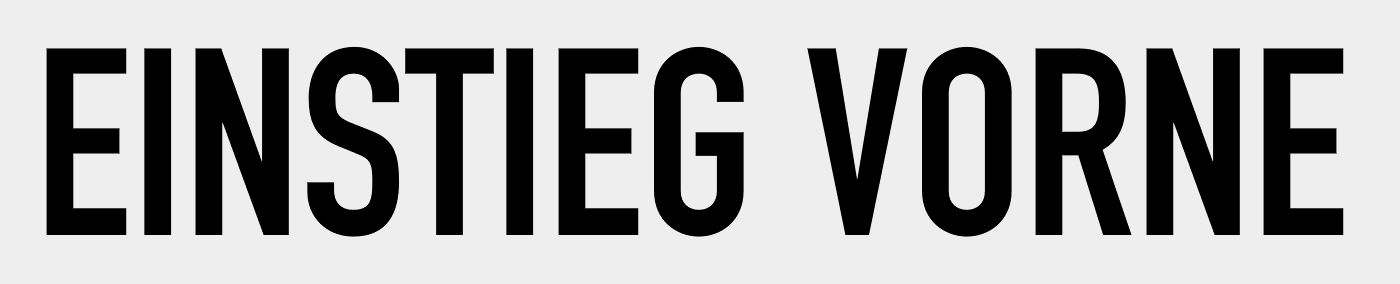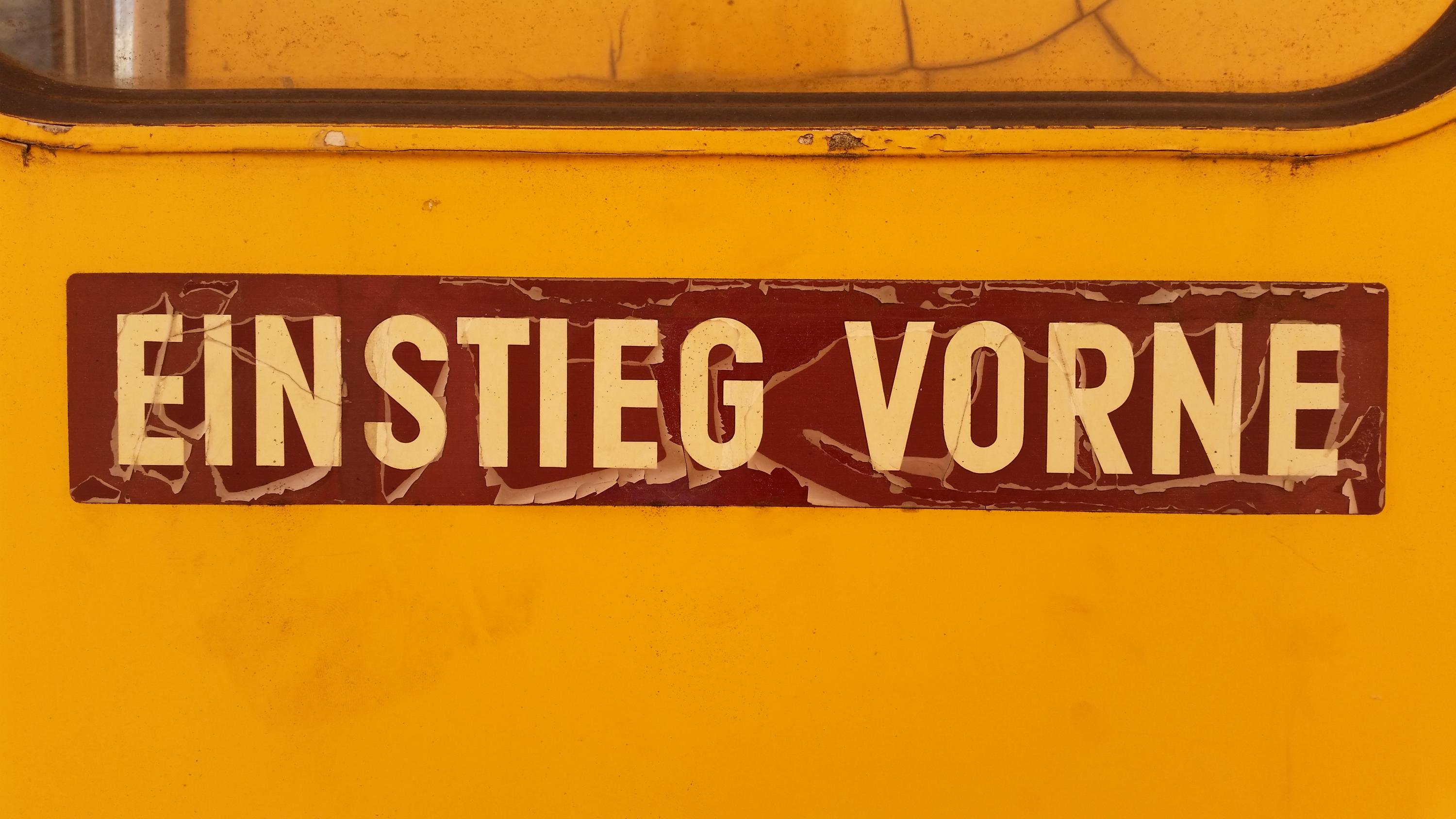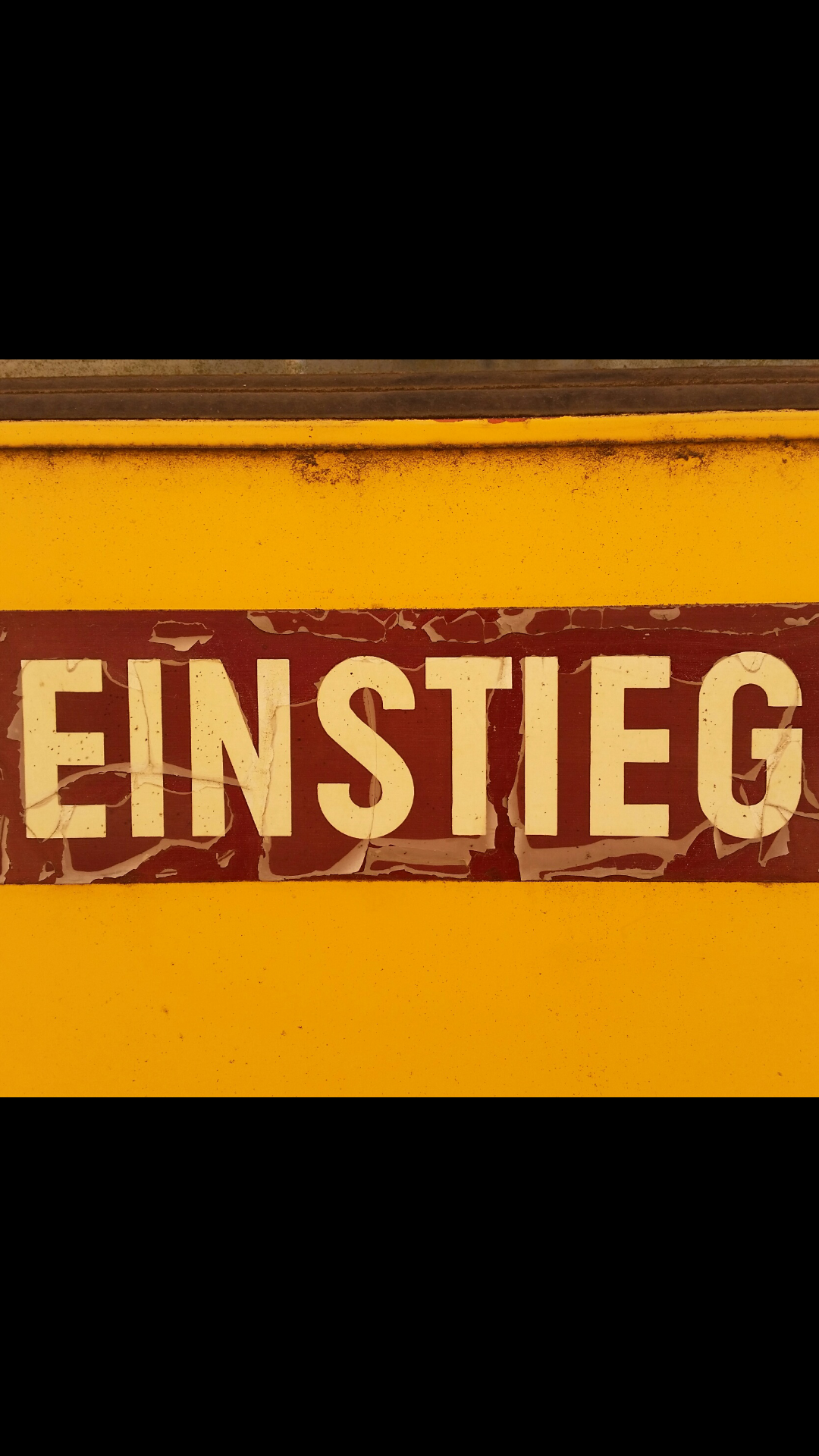
Postbus Österreich aussen 60er-90er Jahre
Screenshot_2017-05-17-07-30-29.thumb.png.7e942f4f3dab041e3cffbc63d778c0f9.pngHallo zusammen, kennt von Euch jemand diese Schriftart, die aussen auf österreichischen Postbussen der 60er bis 80er Jahre angebracht war? Freue mich über alle Hinweise.
Und ich habe mich ein bisschen inspirieren lassen...
Die scheint ja perfekt zu passen. Ist das eine Eigenkration oder hat die ein Vorbild? Nur das R scheint nicht ganz zu passen.
Das ist eine Eigenkreation etwas frei nach Deinen Bildern (drum auch der Name PostBus), aber am R kann  man noch feilen.
So total kann man ja bei etwas schiefen Bildern schlecht halten und Glyphen, die eben in der Vorlage gar nicht enthalten sind, hab ich halt dazu erfunden.
Grundsätzlich sind Schriften, die eben nicht auf Papier gedruckt waren in dieser Zeit oft frei gestaltete Eigenentwicklungen, sofern nicht eine bestimmte Normschrift vorgeschrieben war.
Na ja, hier habe ich mir eigentlich eine kleine Ferkelei erlaubt, und per OpenType einfach das Wort Taxi durch Postbus ersetzt. Ich dachte mir, dass in der Schrift kaum je Jemand das Wort Taxi schreiben wird, und wenn, zumeist nicht in einer OpenType-fähigen Anwendung - und wenn doch, kann calt ja abgeschaltet werden